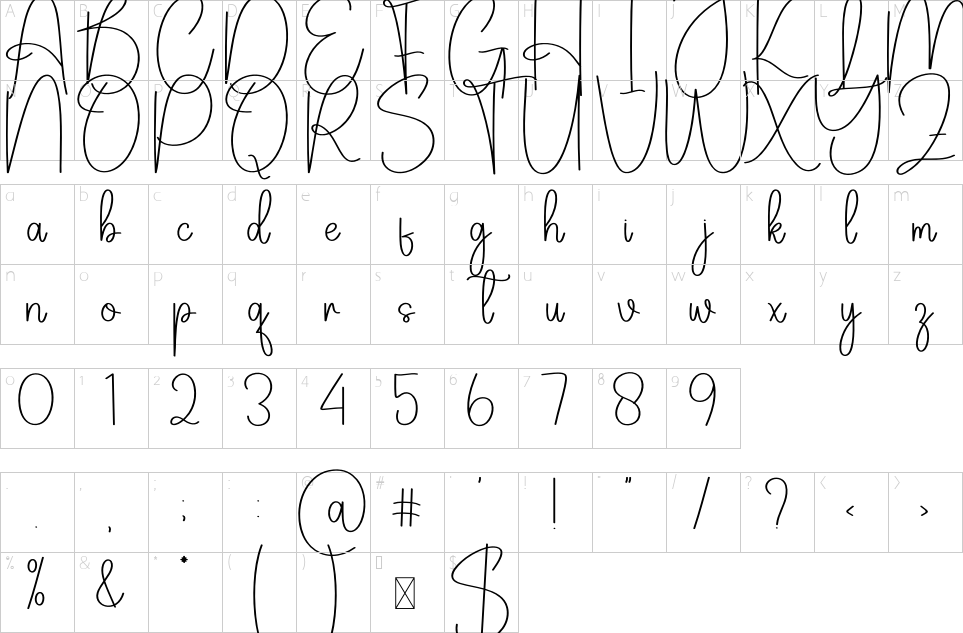
A Jourdy Signature é uma fonte elegante e moderna que traz um toque sofisticado às suas criações digitais. Desenvolvida por William Jhordy, essa fonte personalizada é ideal para assinaturas de e-mail, cabeçalhos de documentos ou qualquer lugar onde você deseja um toque singular e profissional. Jourdy Signature foi projetada com um design elegante e facilmente personalizável, tornando-a uma escolha perfeita para quem busca uma fonte grata para uso pessoal ou profissional. Com sua alta popularidade, já foram baixadas 581 vezes, demonstrando seu valor e qualidade. Descubra por si mesmo como Jourdy Signature pode enriquecer seu design digital.